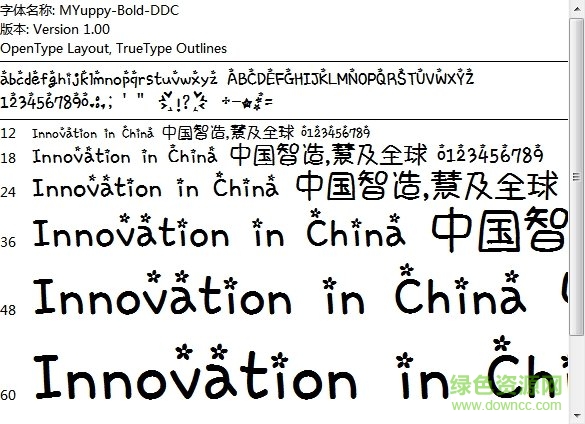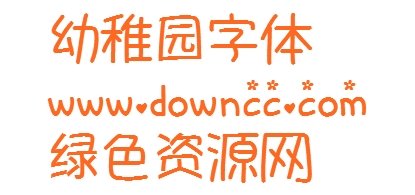
幼稚園字體ttf
幼稚園字體ttf是一款非常童真可愛(ài)的幼兒園字體,讓文字間充滿(mǎn)可愛(ài)的小花兒,給孩子帶來(lái)更加活潑的視覺(jué)體驗(yàn),吸引孩子的注意力,綠色資源網(wǎng)誠(chéng)意推薦!
幼稚園字體字體介紹
幼稚園體字體是一款POP風(fēng)格的卡通字體,英文和數(shù)字還加上了漂亮的卡通花圖案,是非??蓯?ài)的一款字體,特別適合喜歡手機(jī)字體個(gè)性一些的朋友在手機(jī)上安裝使用。
幼稚園字體
幼稚園字體有著憨厚可愛(ài)的呆萌風(fēng)格,字跡清晰有著極佳的視覺(jué)呈現(xiàn),而文字中點(diǎn)綴的小花朵圖案,讓你的平面設(shè)計(jì)、包裝設(shè)計(jì)更加親民。